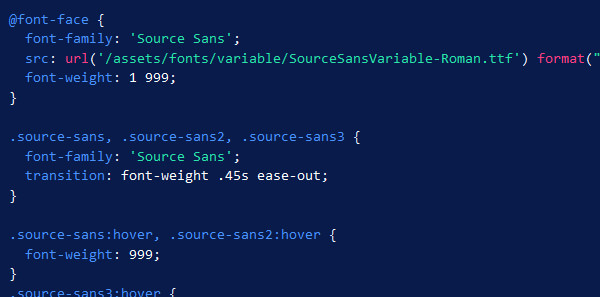
Variable Fonts: Starter Guide
Variable Fonts sprechen für einen variantenreichen Umgang mit Schrift. Der Start mit den interpolierbaren OpenType-Fonts kann jedoch mit Hürden versehen sein. Daher kommen hier einige hilfreiche Tipps, Downloads sowie Hinweise auf Tutorials und Beiträge, die sich intensiver mit Variable Fonts auseinandersetzen.
Vor- und Nachteile von Variable Fonts
Das Praktische an Variable Fonts ist, dass lediglich eine einzige Font-Datei benötigt wird. Diese verhält sich wie viele Fonts, denn alle Varianten der Schrift sind bereits enthalten. Neben unterschiedlichen Strichstärken lässt sich durch Interpolation beispielsweise die Breite und ggf. auch die Neigung individuell einstellen.
Diese „große Freiheit“ will jedoch richtig genutzt werden. Wenn mehrere hundert Varianten einer Schrift zur Verfügung stehen, ist typografisches Fingerspitzengefühl gefragt. Schriftmischungen können sich erheblich aufwändiger gestalten. Zudem benötigen Webfonts in der Regel nicht den vollen Umfang mit allen Varianten der Schrift. Die Dateigröße spielt schließlich auch eine entscheidende Rolle.
Außerdem wird oft nicht sofort ersichtlich, wo sich Strichstärken und Co. in Software-Programmen einstellen lassen und welche Apps das Fontformat und die OpenType-Technik überhaupt unterstützen. Daher kommt hier ein kleiner Starter Guide mit nützlichen Tipps und Ressourcen rund um Variable Fonts.
Variable Fonts in InDesign nutzen
Variable Fonts sind in InDesign – wie andere Schriften auch – über das Zeichen-Fenster erreichbar (Fenster -> Schrift und Tabellen -> Zeichen). Dieses lässt sich alternativ auch mit dem Tastaturkürzel „Strg+t“ (Windows) bzw. „Cmd+t“ (Mac) aufrufen.
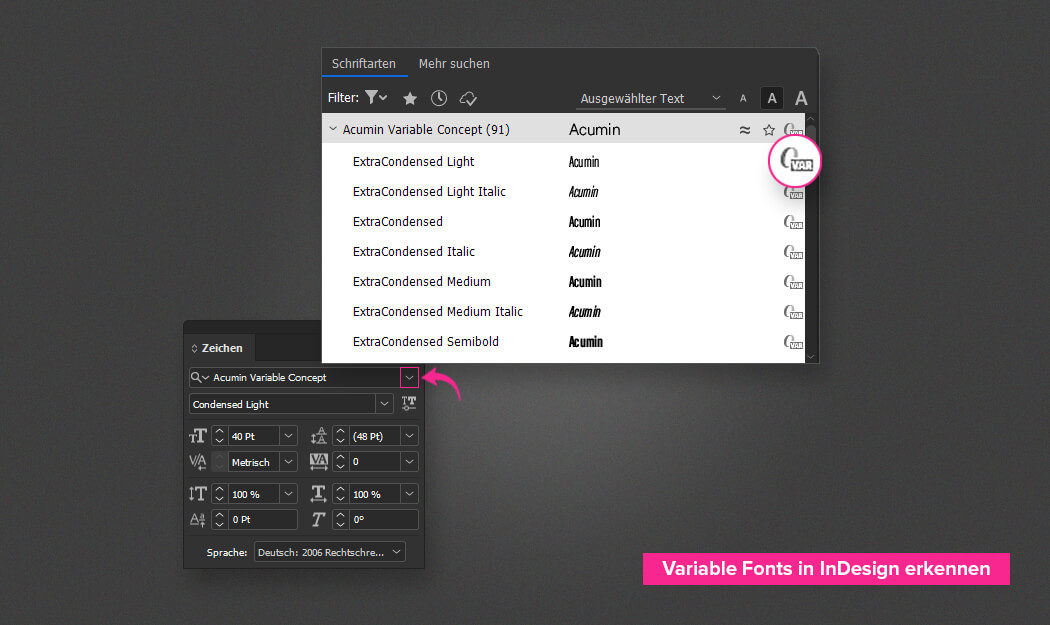
Erkennbar sind die Variable Fonts über das kleine Icon (großes „O“ mit „VAR“ davor) ganz rechts im Fenster. Je nach Font sind bereits einige Varianten direkt anwählbar. Möchte man jedoch individuelle Einstellungen vornehmen, dann klickt man einfach den kleinen Button neben dem Schriftmenü an.
Daraufhin öffnet sich ein Fenster, in dem sich per Schieberegler eigene Einstellungen vornehmen lassen. Wie viele Anpassungen möglich sind, hängt vom jeweiligen Variable Font ab. Einige erlauben lediglich die Änderung der Strichstärke, andere hingegen bieten beispielsweise zusätzlichen Zugriff auf die Interpolation der Breiten-Achse oder der Schrägstellung.
Wie schon in InDesign, lassen sich Variable Fonts ebenfalls in Photoshop am entsprechenden Icon im Fenster „Zeichen“ ausmachen (siehe Abbildung). Das Fenster kann über das Menü „Fenster -> Zeichen“ aufgerufen werden.
Um die Achsen eines Variable Fonts einzustellen, ist jedoch noch ein weiteres Fenster erforderlich. Über „Fenster -> Eigenschaften“ lassen sich im Abschnitt „Zeichen“ individuelle Einstellungen vornehmen. Je nach Umfang des Variable Fonts kann beispielsweise per Schieberegler oder im entsprechenden Eingabefeld Einfluss auf die Strichstärke, Breite oder Schrägstellung genommen werden.
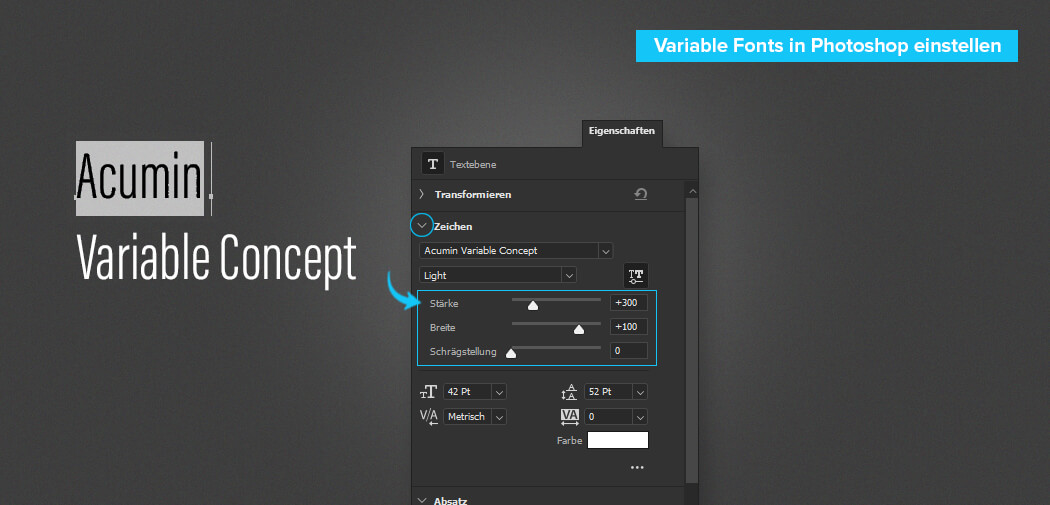
Die Handhabung der Achsen ist praktisch identisch wie in InDesign: Über den kleinen Button neben dem Schriftmenü lässt sich ein Fenster öffnen, in dem sich Strichstärke und Co. per Schieberegler individuell anpassen lassen. In der entsprechenden Fontdatei ist hinterlegt, welche Achsen zum Variieren freigegeben sind. Das können bei dem einen oder anderen Variable Font mal mehr oder weniger sein.
Detaillierte Einführungen
Um ein möglichst großes Spektrum abzudecken, kommen hier einige Verweise auf Beiträge, die sich detaillierter mit variablen Schriften auseinandersetzen und die einen oder anderen Zusatzinformationen enthalten:
Beitrag über Variable Fonts im Typolexikon
Das Typolexikon ist eine Fachenzyklopädie zur Typografie. Der deutschsprachige Beitrag von Wolfgang Beinert geht ausführlich auf Variable Fonts ein und liefert zudem auch einige Thesen.
Die Evolution der Typografie
Jason Pamental schreibt über die Evolution der Typografie und beleuchtet in seinem Beitrag die Vorzüge der neuen Font-Technologie:
Die neuen Möglichkeiten mit Variable Fonts
Ralf Herrmann gibt auf Typografie.info einen Überblick über die 2016 eingeführte Technik und geht zudem auf Software-Unterstützung sowie Installation von variablen Schriften ein.
Very Able Fonts!
Eine visuelle Untersuchung des gestalterischen und kreativen Potenzials von Variablen Fonts liefert Philip Walch in seinem Beitrag, der im Blog von zeroseven.de erschienen ist.
Beispiele und detaillierte Infos von TypeNetwork
Mit Beispielen und englischsprachigen Erklärungen wartet TypeNetwork auf. Auf mehreren Seiten bzw. Kapiteln wird sich ausführlich den variablen Schriften gewidmet.
Mozilla Variable Fonts Guide
Mozilla informiert ausführlich über die Verwendung von variablen Schriften.
Recursive